1968〜1975年に日本通信美術学園でレタリングを学んでいた頃の作品を紹介するページ
勉強中の生徒や卒業生が対象のコンテストが随時開催されていて、そこに出品したもの。
日美展* は年に1回、スタジオ紙上展* は年に4回開催されていた。
日美レタリング教室は夜間の通学部。基本科が週1で6ヶ月、研究科は週1で3ヶ月だった。
すべて課題があり、当時はパソコンなどないから紙の上に製図ペンや筆を使って手描きした。
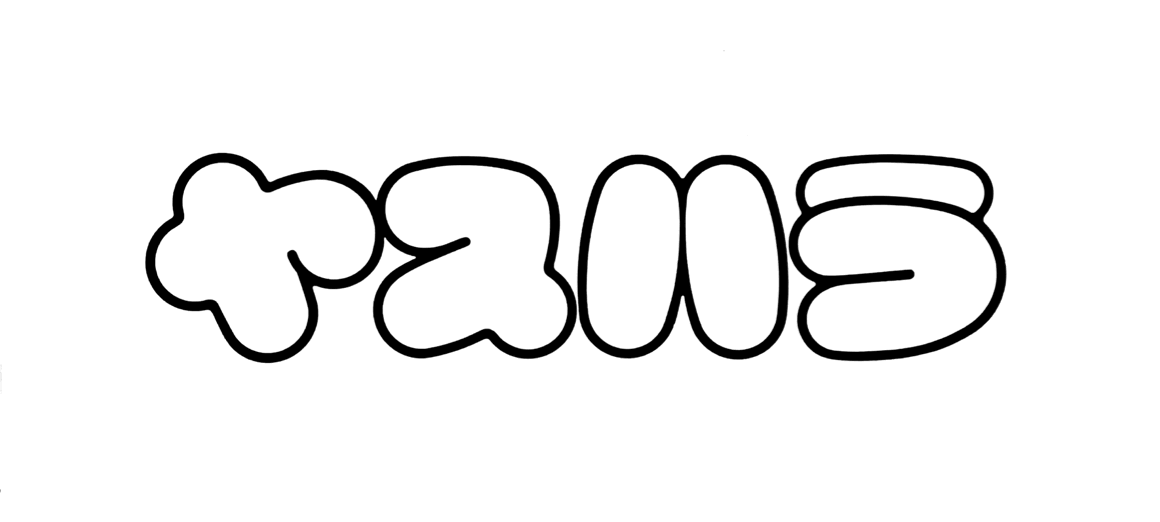
1975 寝具店 35回スタジオ紙上展
ふっくらと柔らかな布団のイメージで文字を描いてみた。
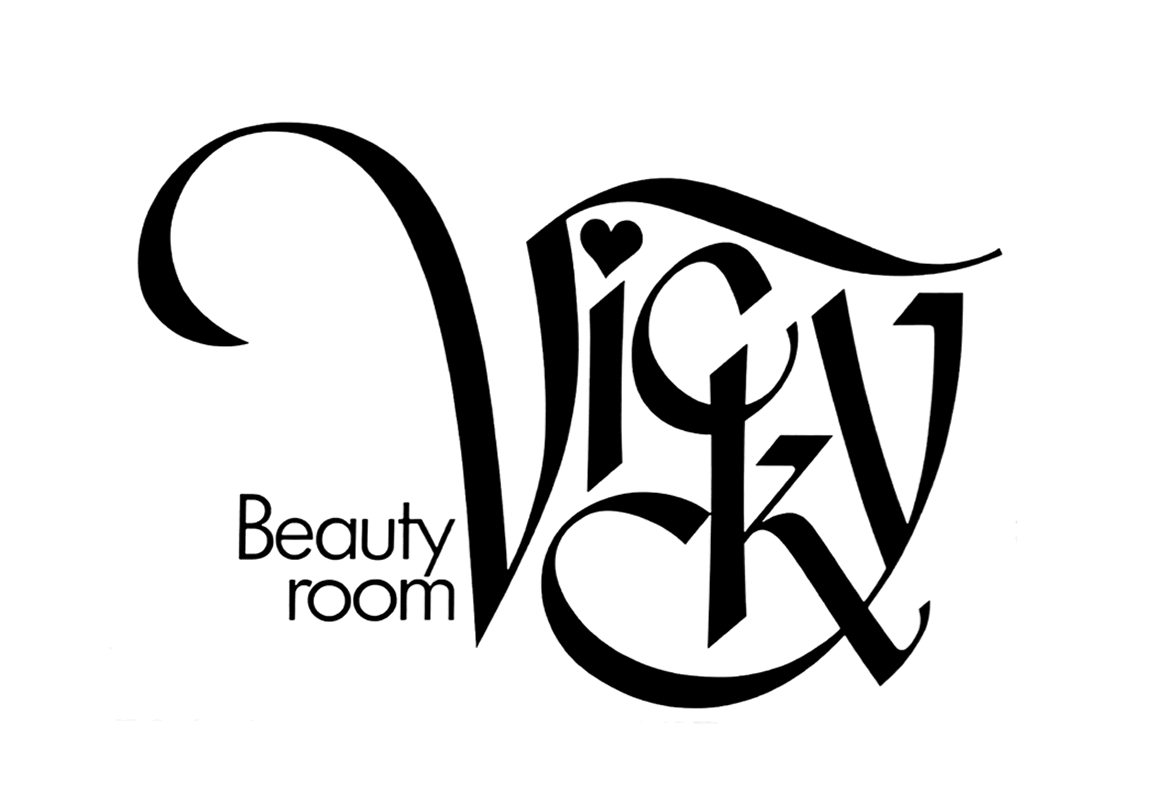
1975 美容院 35回スタジオ紙上展
風になびく髪を表現したつもりだが「c」と「k」の交差した部分が「q」に見えてしまう欠陥あり…。
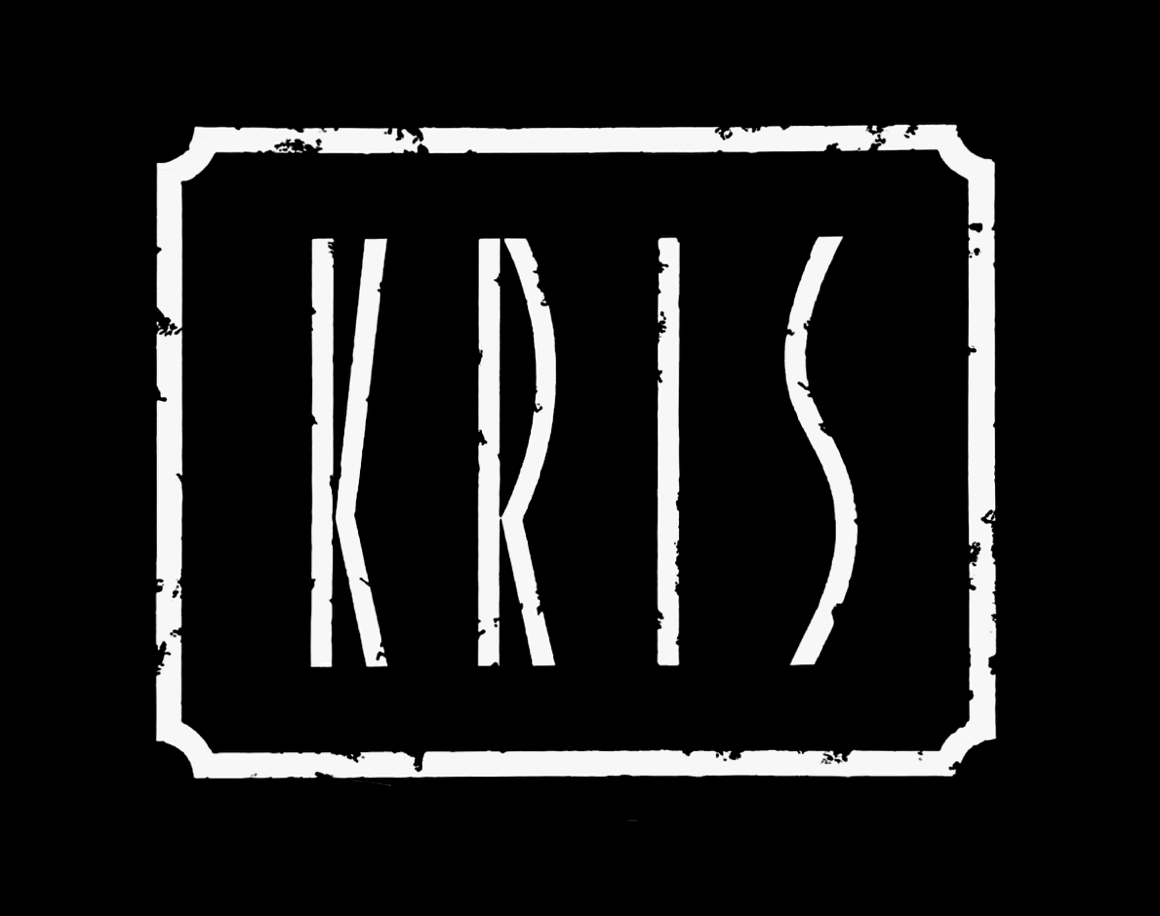
1975 高級毛皮店 35回スタジオ紙上展 金賞(23才)
縦長の文字と字間を開けることで、高級感を出そうとした…。
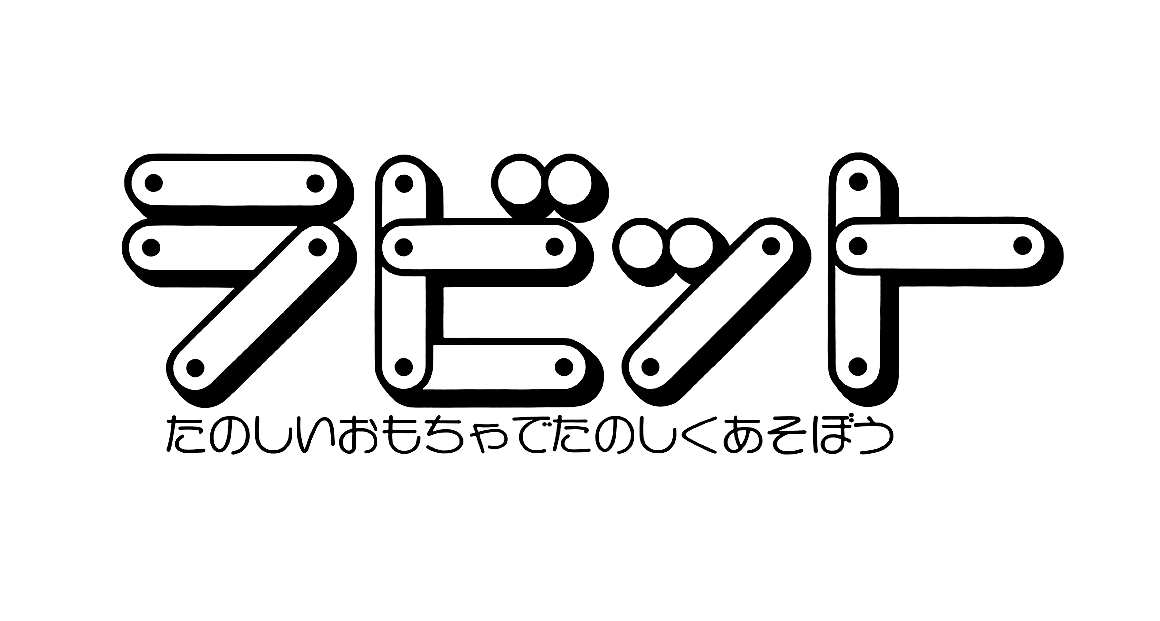
1974 玩具店 33回スタジオ紙上展 銀賞(23才)
幼い頃、木製の棒パーツをネジで組み合わせて遊ぶ玩具が家にあり、それで遊んだ記憶からこんなデザインになった。
のちに、ピノキオというカタカナ書体の元になった。ロゴ下の文字はゆたんぽん書体。
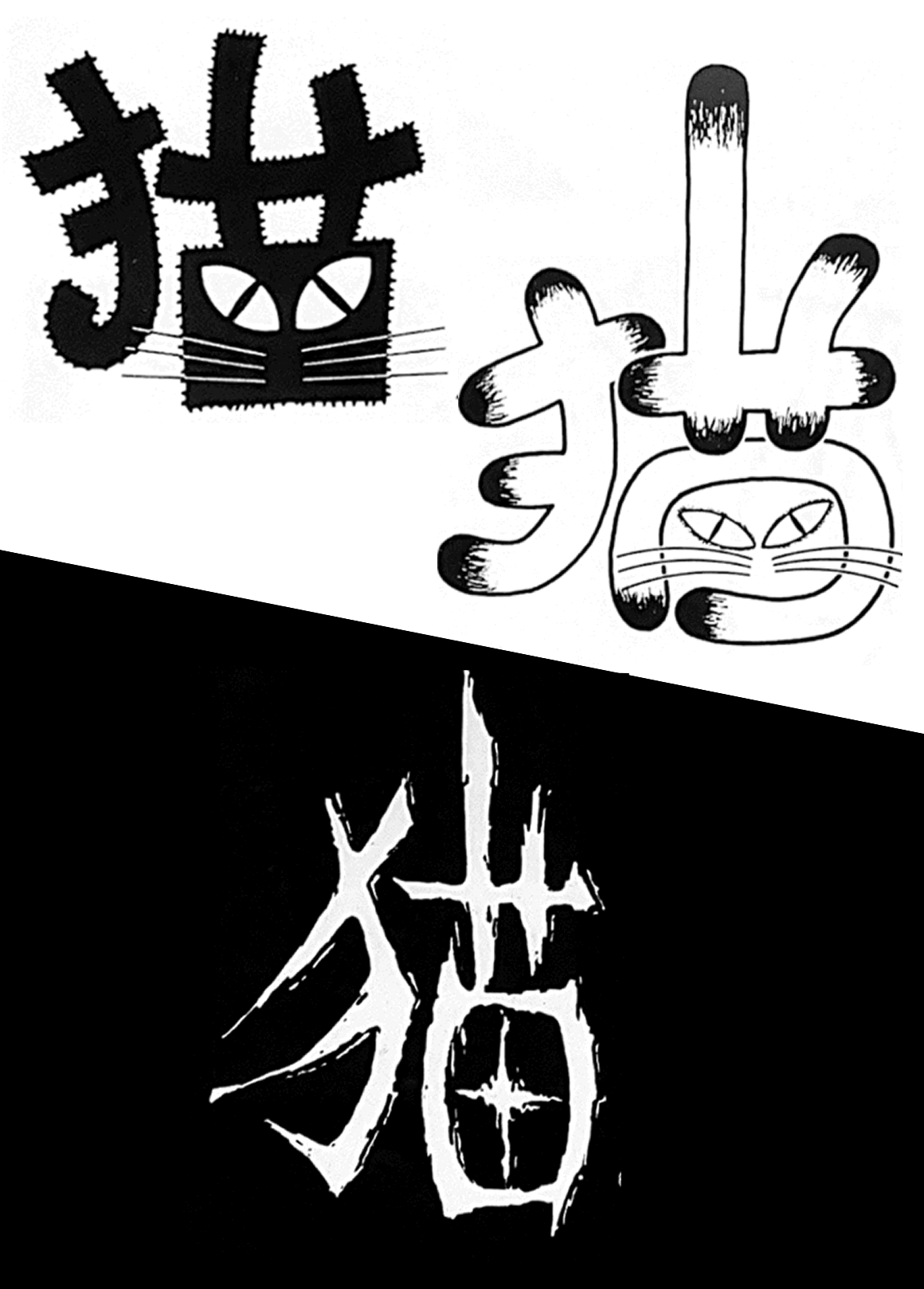
1974 猫のイメージ 32回スタジオ紙上展 特選(23才)
野良猫・室内猫(シャム?)・化け猫かな…。
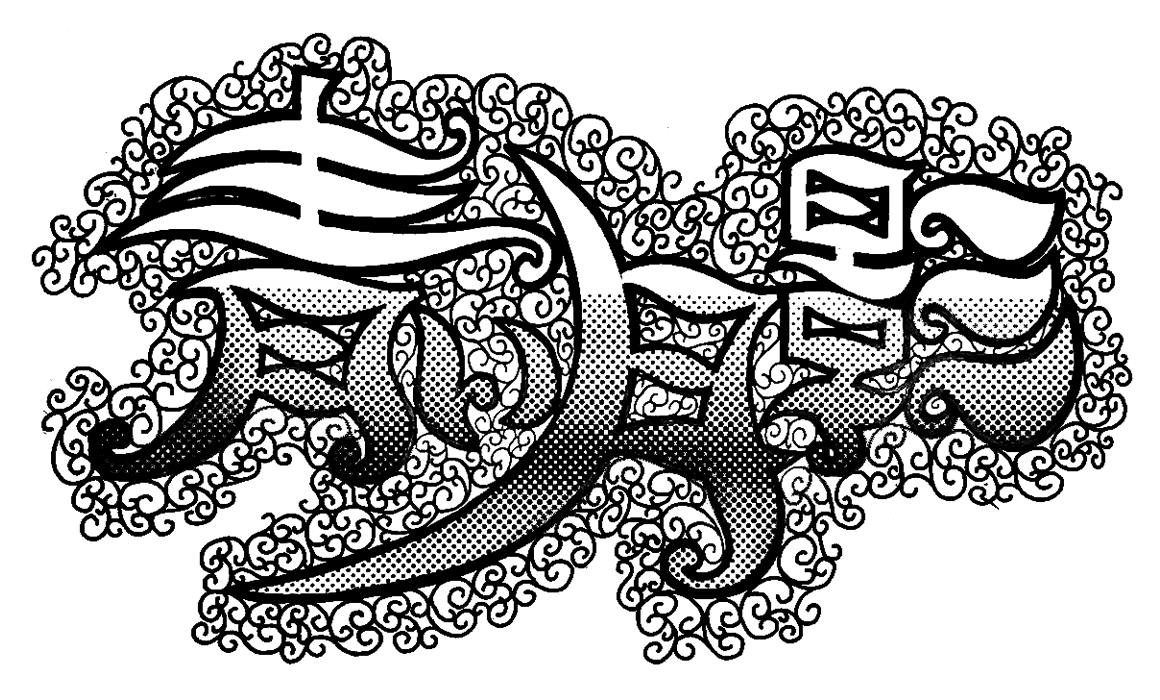
1974 映画題名 33回スタジオ紙上展
これは下書きというか、出品前のテスト版。
実際の作品はカラーで、背景は茶系、いまスクリーントーンが貼られている文字の中には、青から緑のグラデーションとなっていた。
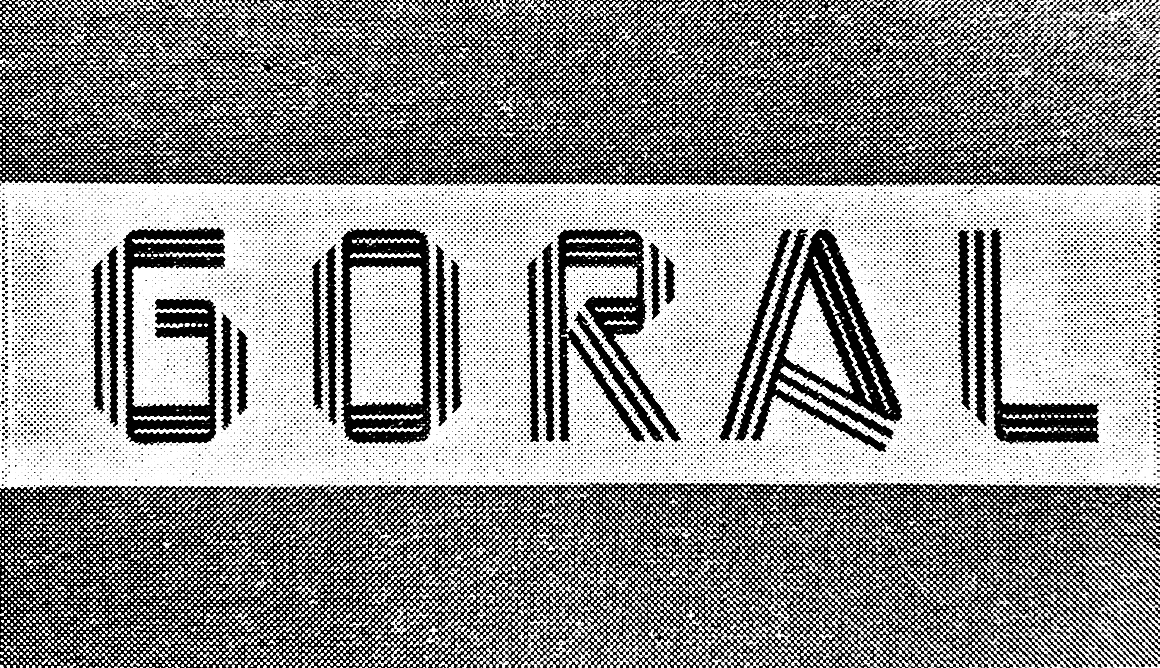
1974 ネクタイ専門店 34回スタジオ紙上展 スタジオ賞(23才)
スタジオ紙に掲載された、この画像しか残っていなかった。
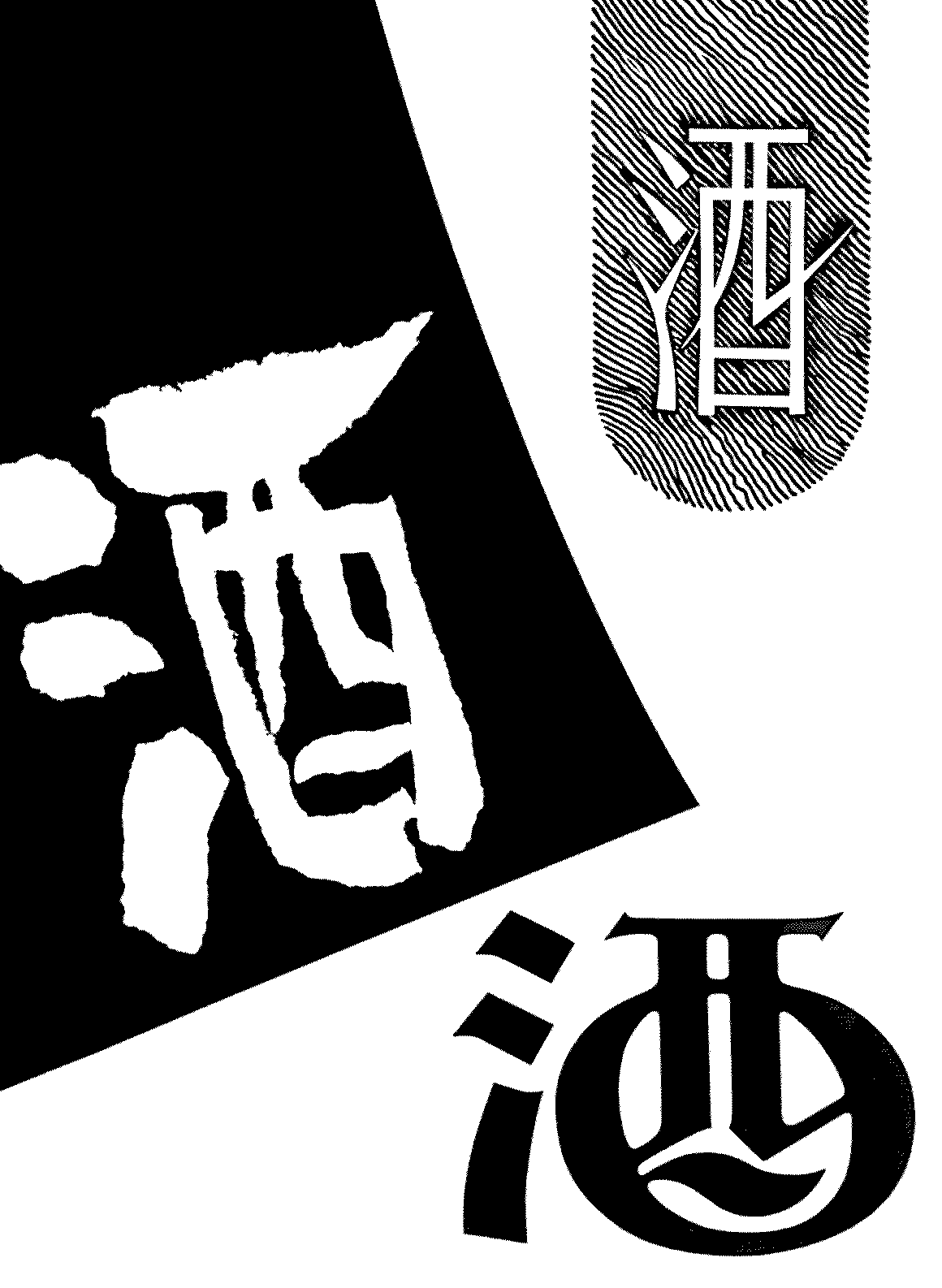
1973 酒のイメージ 31回スタジオ紙上展 特選(22才)
日本酒・居酒屋の暖簾・ウイスキー瓶(当時流行っていたサントリーオールド)をイメージ。
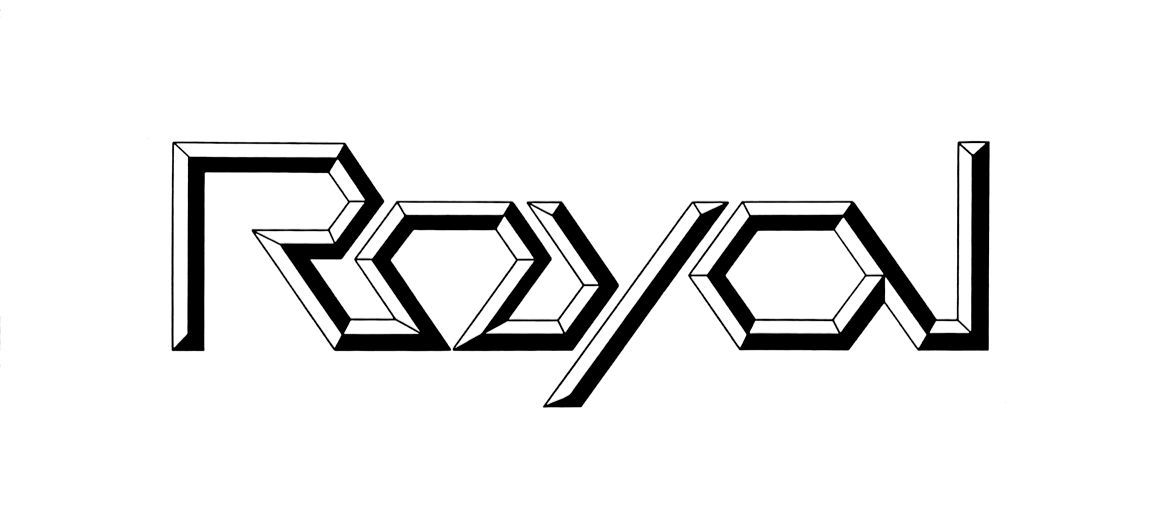
1973 貴金属店 27回日美展
精密にカットされた宝石や金属の雰囲気を表現。
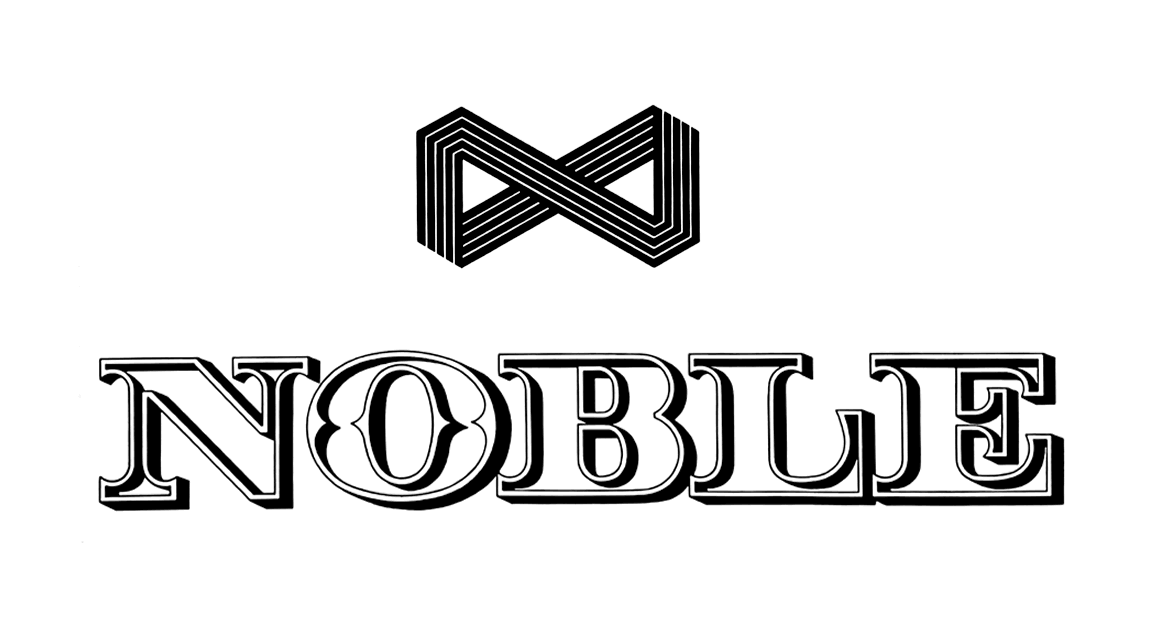
1973 高級紳士衣服店 ?回スタジオ紙上展 特選(21才)
シンボルは「N」の文字を蝶ネクタイのイメージにしたもの。「NOBLE」こういうスタイルを手描きするのは大変だった。
小さな曲線部は、スプリングコンパスという特殊な製図器具を使っている。
文字が水辺に並ばず、すこし湾曲しているのは、記録したカメラとか印画紙のせい…。
1973 数字書体 ?回スタジオ紙上展(21才)
このスタイルでは数字しかデザインできなかった…のだな、多分。
1972 特別課題 26回日美展 マックスファクター賞(21才)
化粧品会社から出された課題。かなりエネルギーをかけて制作した。
1972 映画題名 23回スタジオ紙上展 スタジオ賞(20才)
SF映画なので、アンドロメダの文字は直線で未来風なイメージに、病原体は有機的な形に…。
よい状態の原図が残っておらず、これはスタジオ紙に掲載されたもの。
1972 鉄道路線名 26回日美展
この年に開業した国鉄(現在のJR)の路線名。「ひかりは西へ」というキャンペーンもあった。
1972 イベント 26回日美展 奨励賞(21才)
たくさんの要素を詰め込んでフェステバル感をだした。ちょっと可愛くなりすぎたかも…。
1972 映画題名 26回日美展(20才)
松本清張の小説が原作のサスペンス映画。
1971 映画題名 29回スタジオ紙上展 特選(19才)
エリザベス・テイラー、リチャード・バートンなどが出演した、エジプトが舞台の歴史映画。
1971 詩文 25回日美展
中原中也の有名な詩の一節だが、原文は「はためくを」なのに、無知な私が勝手に「の」を加えてしまった…失敗作。
1971 映画題名 25回日美展 特選
イタリアを舞台にした青春映画。主題歌の「Che
vuole questa musica stasera」は、お笑い芸人ヒロシがBGMとして使っている。
内容など調べずに題名から勝手に想像して作ってしまった…。